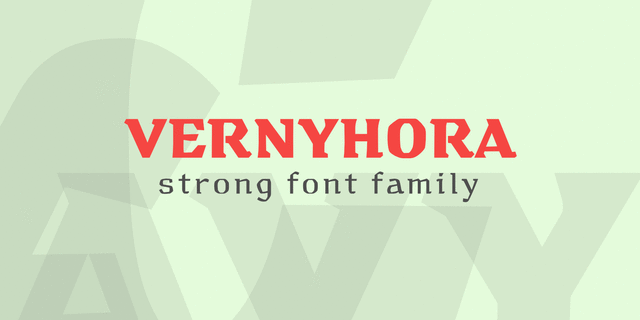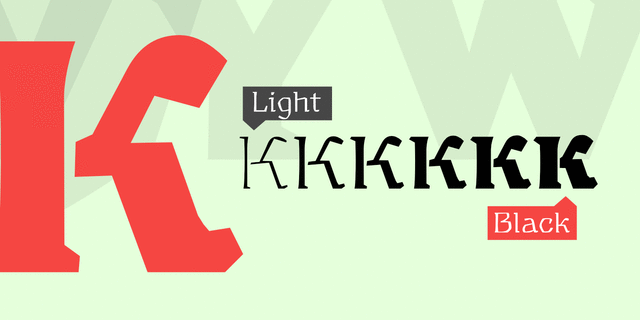
Винтажное акцидентное шрифтовое семейство Вернигора. Шрифт предназначен для мест, где буквы должны передавать сильный характер, надежность и историческую значимость. Гарнитура имеет 6 насыщенностей и содержит расширенную кириллицу и латиницу. Также имеется альтернативный набор символов для староукраинского алфавита. Шрифт будет отлично смотреться на вывесках государственных учреждений. Изначально Вернигора предназначался для туристических городов, с историческими кварталами, чтобы обозначать въезд в город. Форма шрифта вдохновлена работами украинских графиков начала 20-го века, таких как Георгий Нарбут и Федор Кричевский. Гарнитура содержит 1 бесплатное начертание Vernyhora Demo EstraBold. Вы можете свободно использовать его, но не разбирать и не издавать шрифт от своего имени. Лицензия на Vernyhora Demo EstraBold: https://creativecommons.org/licenses/by-nd/4.0/deed.uk Шрифт Вернигора разработал Богдан Гдаль в 2017 году.
твердый, свободный, тонкий, жесткий, четкий, исторический, самобытный, характерный, оригинальный, резкий, острый, колоритный, артистичный, художественный, динамичный, ремесленный, выразительный, крафтовый, рубленый, холодный, ледяной, стеклянный, хрупкий, прозрачный, колючий, ломаный, племенной, артизанальный, худой, казацкий, вольный, гордый, воинственный, храбрый, бравый, мужественный, сильный, темпераментный, мотивирующий, активный, амбициозный, суровый, грубый, железный, рабочий, посконный, сермяжный, деревенский, религиозный, экологичный, добротный, устойчивый, смелый, этничный, натуральный, традиционный, ностальгический, убедительный, уверенный, рукотворный, консервативный, природный, мятежный, героический, каменный, тяжелый, броский, заметный, мощный, массивный, солидный, настойчивый, черный, тесный, стальной